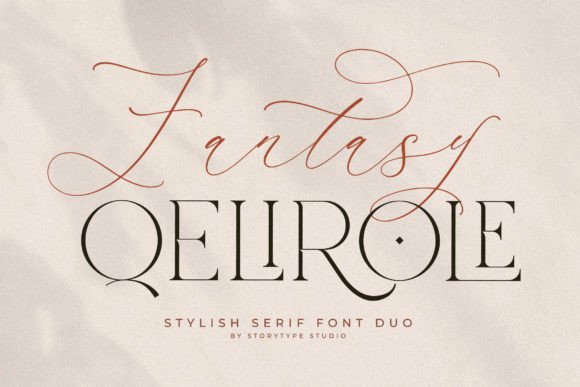
Fantasy Qelirole Duo
適切なデザイン要素を見つけるのは難しい場合がありますが、Fantasy Qelirole Duoは作品を即座に引き立てる優れたコレクションを提供します。
POD(オンデマンド印刷)製品、結婚式の招待状、またはソーシャルメディアのグラフィックを作成している場合でも、Fantasy Qelirole Duoは理想的です。